今回はアニメやマンガ・同人誌・ドラマ・Youtubeなどのタイトルにそののままベタ打ちで使ってもロゴっぽくなる「タイトルロゴ」にぴったりなおすすめの日本語フリーフォントをまとめてみました。
タイトルロゴを作りたい場面など、ゼロから作るのは少し大変なので、ベタ打ちするだけでオリジナリティを感じるロゴのようになるフォントを中心に選んでみました。
アニメやマンガ・同人誌・ドラマ・Youtubeなどでオリジナルのタイトルロゴが作りたい方におすすめの個性的なフォントばかりです。
「タイトルロゴ」にぴったりな日本語フリーフォントまとめ
以下のサンプル画像は、本記事で紹介しているフォントを使用して、小説・同人誌・アニメ・マンガなどのタイトルロゴをサッと作成してみました。
このようなタイトルロゴに使えるフォントを選んでみたので参考ください!
源界明朝
源界明朝は、かすれているような加工されている明朝体フォント。
かすれている感じが、サバイバル系、ミリタリー系、アクション系、など幅広いシーンで活躍できそうな素敵なフォントです。
瀞ノグリッチ
瀞ノグリッチは、グリッチ加工が施されたフォント。
映像が乱れたような雰囲気を持つイメージは、SF系や電子系のジャンルと相性が良さそう。
異世明
異世明は、異世界に飛ぶ時にぐにゃっと歪む瞬間を表現したフォントです。
文字の歪みが少しユニークなデザインになっているので、異世界系・魔界系・アクション系などさまざまなシーンで活躍できるタイトルロゴになりそうです。
零ゴシック
零ゴシックは、パリーンとガラスが割れたような加工がユニークなフォントです。
タイトルロゴにはぴったりなインパクトあるデザインです。かっこいい!
コーポレート明朝
コーポレート明朝は、少し縦長なほっそりとした明朝体フォント。
上記で紹介しているような遊んでいるフォントではなく、細くスマートでスタンダードな明朝体ですが、少し長体に変形されているのでカッコいい雰囲気を出すタイトルロゴでも相性が良いです。
バナナスリップ
バナナスリップは、太くて強い骨格と、微かな可愛らしさが絶妙なフォントです。堅苦しくはしたくないし、可愛すぎるのもちょっと違う、みたいなシーンのときにはピッタリなフォントです。
アニメや同人誌などさまざまシーンで活躍できるフォントです。
トガリテ
トリテガは、トゲトゲしたフォルムはインパクトがあるので、タイトルやロゴなどに使ってみると面白い仕上がりになりそうです。
キルゴ
キルゴは、ゴツゴツした極太系フォントです。
もともとはアニメにロゴを参考に作られてたフォントなので、アニメやポップな印象をタイトルロゴで作り出しときにはぴったりのフォントです。
叛逆明朝
叛逆明朝は、ゴスロリ系とブラックレター系が混ざったようなフォント。
ダークファンタジー系と相性がとっても良さそう。本当にベタ打ちするだけで、アニメ系のロゴのようにも使えるのでとっても優れているフォントになっています。
暗黒ゾン字
暗黒ゾン字は、ホラーの雰囲気を作りたい場合に使えるフォントです。
昔の怪奇映画のタイトルやお化け屋敷の看板のようなイメージで作られたフォント。そのままですが、ホラー系のジャンルにはぴったりです。
数式フォント
数式フォントは、算数・数学のテストによくあった図式の記号を随所に取り入れたユニークなフォント。
一文字一文字細かいところまでデザインされているので、見ているだけでも楽しいフォントです。
セリフゴシック
セリフゴシックは、文字先にどっしりとしたセリフ装飾が付けられているデザインゴシック体のフォントです。このセリフ装飾が付いていることで、高貴やエレガントを感じさせるデザインです。
あおさぎR
あおさぎRフォントは、明朝体ベースのフォントですが、遊びこころがあるので固くなりすぎずにポップで柔らかい印象がある明朝体です。哀愁やレトロ感を感じる表情をもつフォントです。
レシートフォント
レシートフォントは、食品パッケージに印字された「賞味期限」の文字を参考にして制作されたデザインフォントです。ドットのみで構成されているデザインなので、他のフォントにはない面白い表現ができるフォントです。
ビルの谷間と高架下フォントは、漢字とひらがな、カタカナのでこぼこ感が可愛いらしいデザインフォントです。ポップなストーリーなラノベタイトルなどにおすすめです。
カクダロン
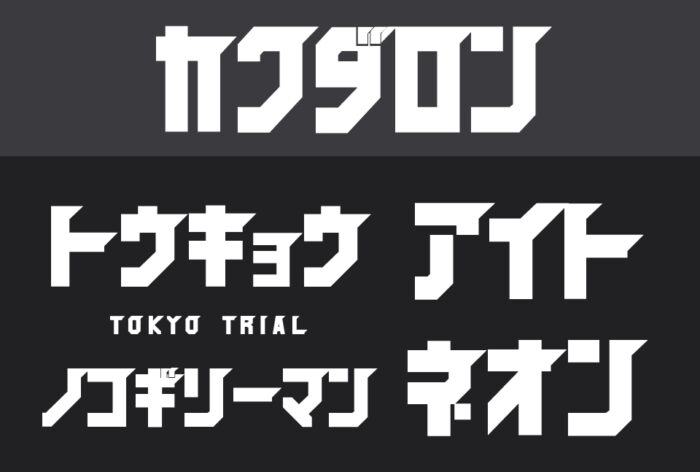
カクダロンフォントは、スピード感を感じる装飾と、無骨で角張ったフォルムが特徴的なデザインフォントです。疾走感を出したいタイトルにぴったりです。
まるこいあす
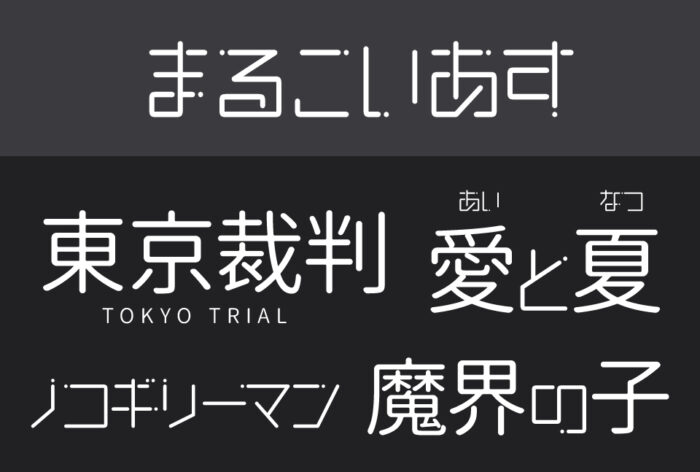
まるこいあすフォントは、漫画・アニメ「恋する小惑星」のロゴをヒントにして制作されたフォントです。流れ星のような装飾がかわいいフォントです。
KazukiReiwa(一樹令和)
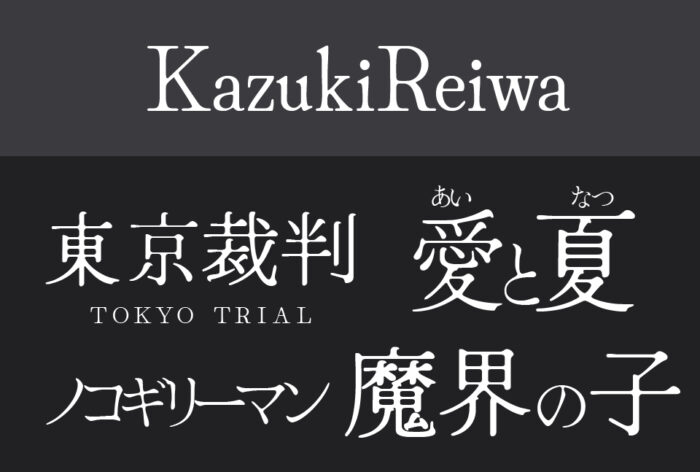
KazukiReiwa(一樹令和)フォントは、墨溜まり加工が施されている上品で、柔らかい印象をもつオールドスタイルの明朝体フォントです。レトロな風合いがストーリーを感じられるフォントです。
FGゼロラバウル
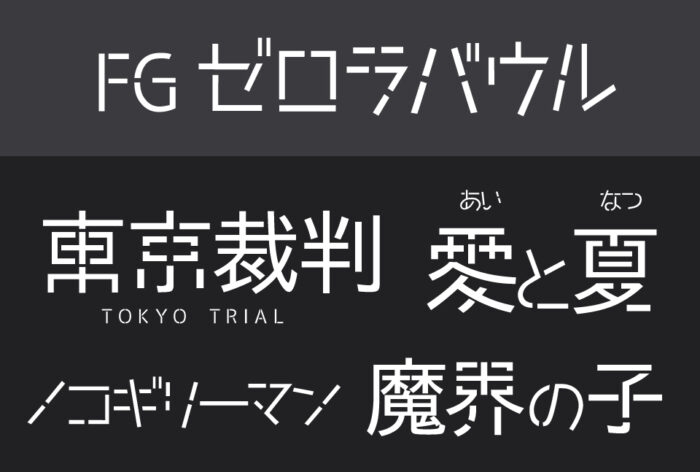
FGゼロラバウルフォントは、零式艦上戦闘機の機体プレートに使われていた文字を再現し、現代風にアレンジされ制作されたデザインフォントです。
ぎっしりフォント
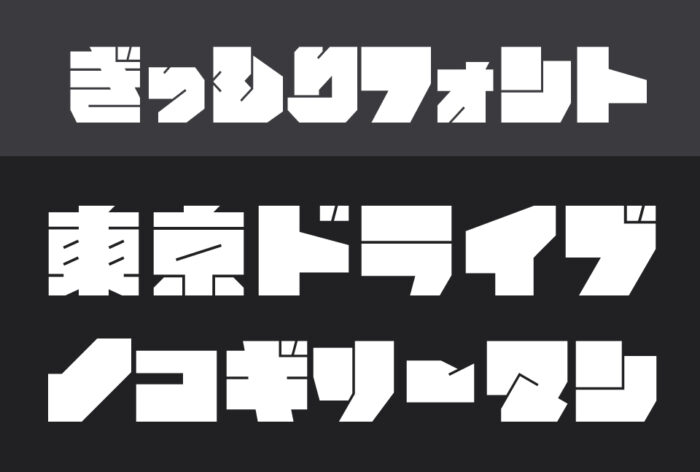
ぎっしりフォントは、直線のみで構成され、正方形でぎっしり詰まっているのが特徴のユニークなフォントです。
源暎きわみゴ
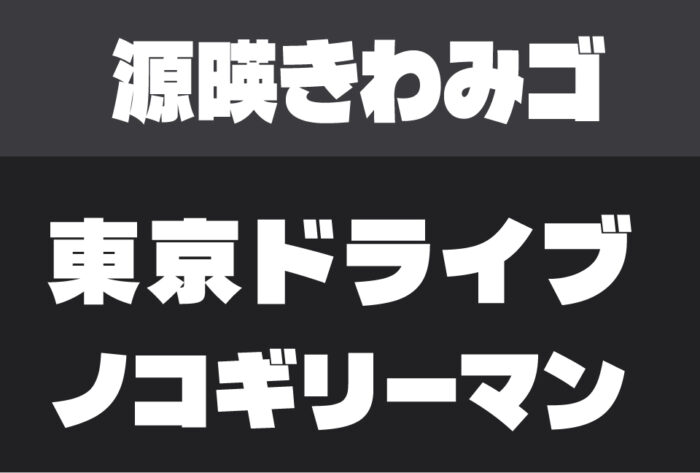
源暎きわみフォントは、超極太フォントで視認性・判読性も高く、強い印象があり、目を引くフォントなので、さまざまなジャンルのタイトルロゴにも適しているフォントです。